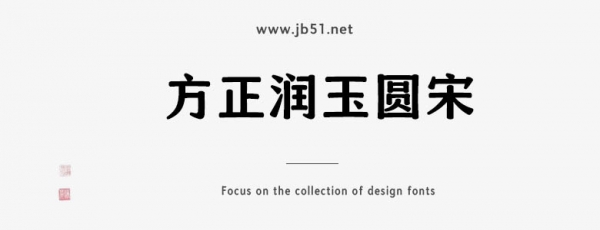
方正潤玉圓宋由方正字庫關秋培設計師出品的藝術字體,字體橫運用向上的弧形設計,豎采用向內(nèi)弧的曲線,長撇筆畫舒緩、溫潤帶有弧度,適合應用于藝術設計、平面宣傳設計、網(wǎng)頁設計,書法等領域。
字體是宋體與圓體之間的調(diào)和,橫運用向上的弧形設計,豎采用向內(nèi)弧的曲線,長撇筆畫舒緩、溫潤帶有弧度,豎鉤融入楷體的圓潤和宋體的速度,使整體的字,具有彈性和張力,字體既有溫潤如玉的男子氣質(zhì),又有蕙質(zhì)蘭心的女子純潔高雅。應用于字體排版,包裝,書籍海報中標題的字體等。